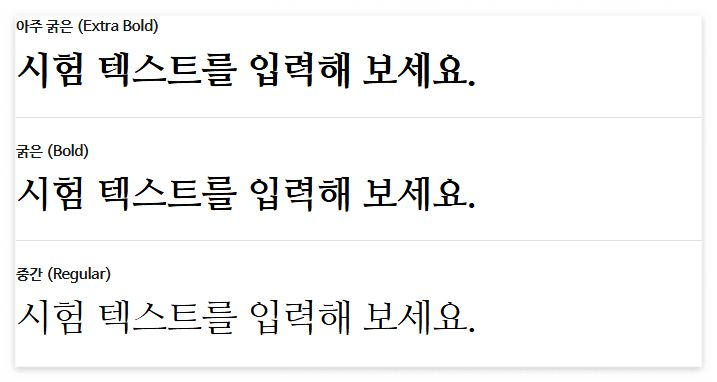
나눔명조 - 전통과 현대를 결합한 고품격 무료 서체 폰트 다운로드
나눔명조는 명조체의 전통적인 미학을 현대적으로 재해석한 글꼴입니다.
붓글씨의 힘을 살리면서도 세련된 직선미를 통해 명쾌하고 정돈된 느낌을 제공합니다.
문서 작성, 출판, 디자인 등 다양한 분야에서 활용할 수 있는 나눔명조의 특징과 활용 방안을 소개합니다.
나눔명조의 특징과 장점
나눔명조는 한글의 아름다움과 현대적 감각을 조화롭게 담아낸 서체로, 명조체 특유의 고급스러움을 살리면서도 실용성을 갖추고 있습니다.
1. 붓글씨와 직선미의 조화
나눔명조는 붓글씨의 힘있는 필체를 바탕으로 글자 끝을 직선적으로 처리해 명조체의 우아함과 현대적 정갈함을 모두 담아냈습니다.
이러한 디자인은 전통적이면서도 명쾌한 인상을 주어 가독성을 높이는 데 탁월합니다.
2. 다양한 굵기 제공
나눔명조는 Extra Bold, Bold, Regular 세 가지 굵기를 제공하여 제목부터 본문까지 다양한 용도로 활용할 수 있습니다.
굵기 옵션 주요 활용 방안
Extra Bold 포스터 제목, 잡지 표지 등 강조 텍스트
Bold 보고서 중제목, 논문 제목 등 명확한 표현
Regular 본문, 소설, 에세이 등 긴 텍스트 작성
3. 폭넓은 문자 지원
나눔명조는 한글 11,172자, 영문 94자, KS 약물 986자를 지원합니다.
이는 문서 작성뿐만 아니라 다국어 콘텐츠 제작과 출판 작업에서도 활용도가 높음을 의미합니다.
4. 고급스러운 디자인과 가독성
나눔명조는 글자 사이의 간격과 크기를 세심하게 설계해 긴 텍스트에서도 가독성을 유지합니다.
특히, 전통적인 명조체의 우아함과 직선적인 간결함이 어우러져 고급스러운 인상을 줍니다.
나눔명조의 활용 방안
1. 출판물과 인쇄물 제작
나눔명조는 책, 잡지, 논문 등 출판물에서 탁월한 선택입니다.
긴 텍스트도 편안하게 읽을 수 있는 가독성과 고급스러운 디자인은 독자의 시각적 만족도를 높여줍니다.
2. 보고서 및 공식 문서 작성
보고서, 제안서, 연구 논문 등의 문서에서도 나눔명조는 그 가치를 발휘합니다.
Regular 굵기를 본문에, Bold 또는 Extra Bold를 제목에 사용하면 깔끔하면서도 전문적인 문서를 완성할 수 있습니다.
3. 디자인 프로젝트
포스터, 배너, 초대장 등 디자인 프로젝트에서도 나눔명조는 효과적입니다.
특히 Extra Bold는 강조 텍스트에 사용하면 독자의 시선을 사로잡는 강렬한 인상을 남길 수 있습니다.
4. 교육 자료 제작
교과서, 강의 자료, 교육 포스터 등 교육 콘텐츠에도 나눔명조는 적합합니다.
가독성이 높은 서체로, 다양한 연령층의 독자가 편안하게 읽을 수 있도록 돕습니다.
나눔명조 사용 후기
나눔명조를 실제로 사용해 보면, 긴 텍스트 작성에도 눈의 피로가 적고, 명조체 특유의 고급스러움이 문서의 품격을 높여줍니다.
특히 보고서 작성 시 Regular와 Bold의 조화를 통해 중요한 부분을 명확히 강조할 수 있어 유용했습니다.
출판물 제작에서도 나눔명조는 독자의 몰입감을 높이는 데 도움을 줍니다.
서체의 정돈된 느낌이 텍스트의 신뢰도를 한층 끌어올리는 효과를 주기 때문에, 많은 전문가들이 이 서체를 추천합니다.
마치며
나눔명조는 전통적인 명조체의 미학과 현대적 실용성을 결합한 글꼴로, 문서 작성, 출판, 디자인 등 다양한 분야에서 활용될 수 있는 고품질 무료 서체입니다.
나눔명조는 당신의 작업에 한층 세련된 품격을 더할 것입니다.